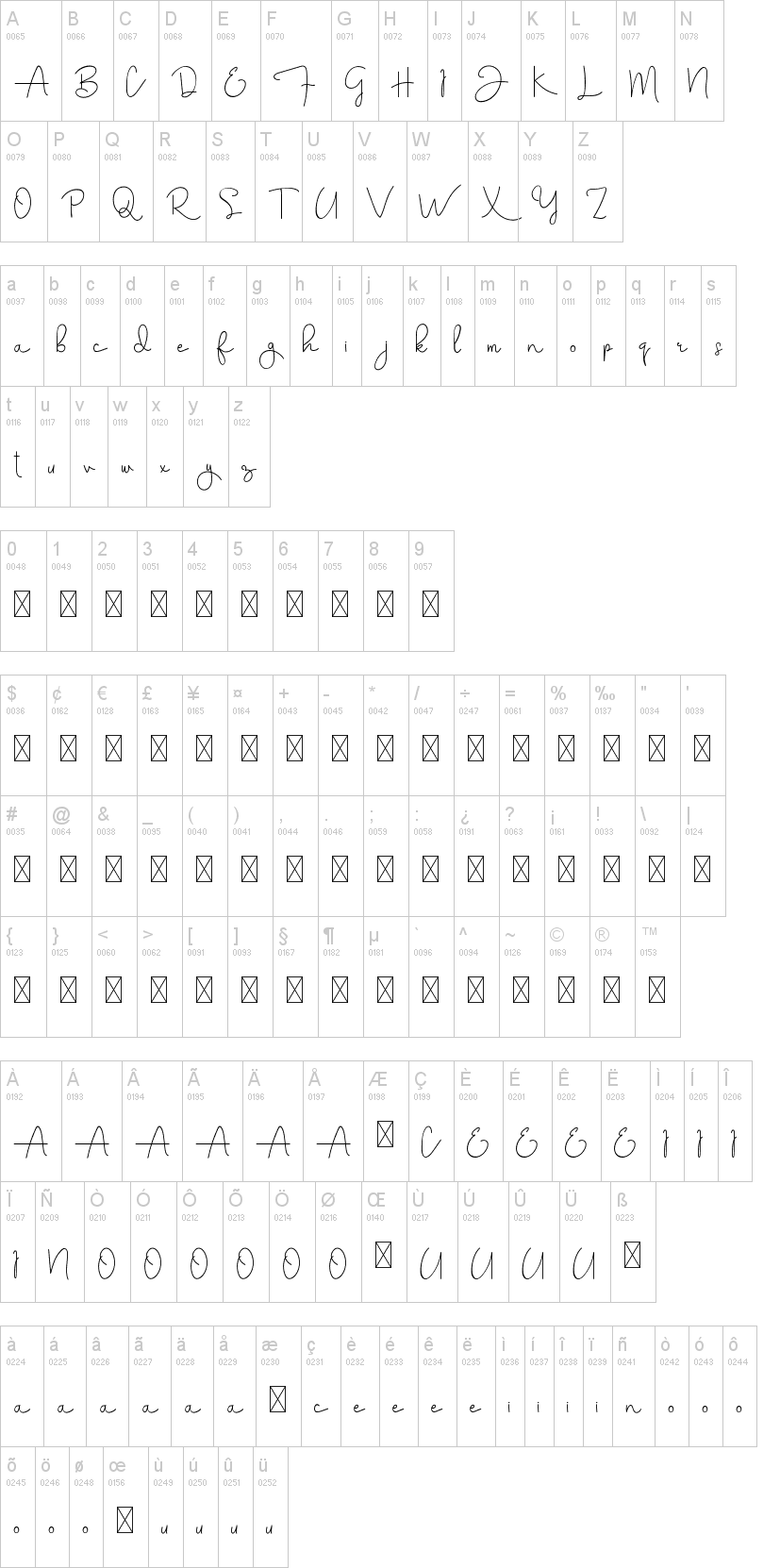
Aghnesta 字体是一款简约的拉丁文字体,它由印度设计师 Aniruddha Paul 创作,于 2019 年发布。Aghnesta 字体拥有清晰的轮廓和细节,具有现代感,同时又保留了传统的印度文字的特点。它有两种字重,分别是 Regular 和 Bold,可以用于各种文字和图形设计,从海报到广告,从标识到网站,以及其他任何需要简约而又富有个性的场景。内容介绍
Aghnesta是一款非常不错的手写艺术字体,具有很好的视觉感,适合于文化类的宣传设计、商业类品牌的广告和产品包装设计以及个性化文字排版等较多场景。